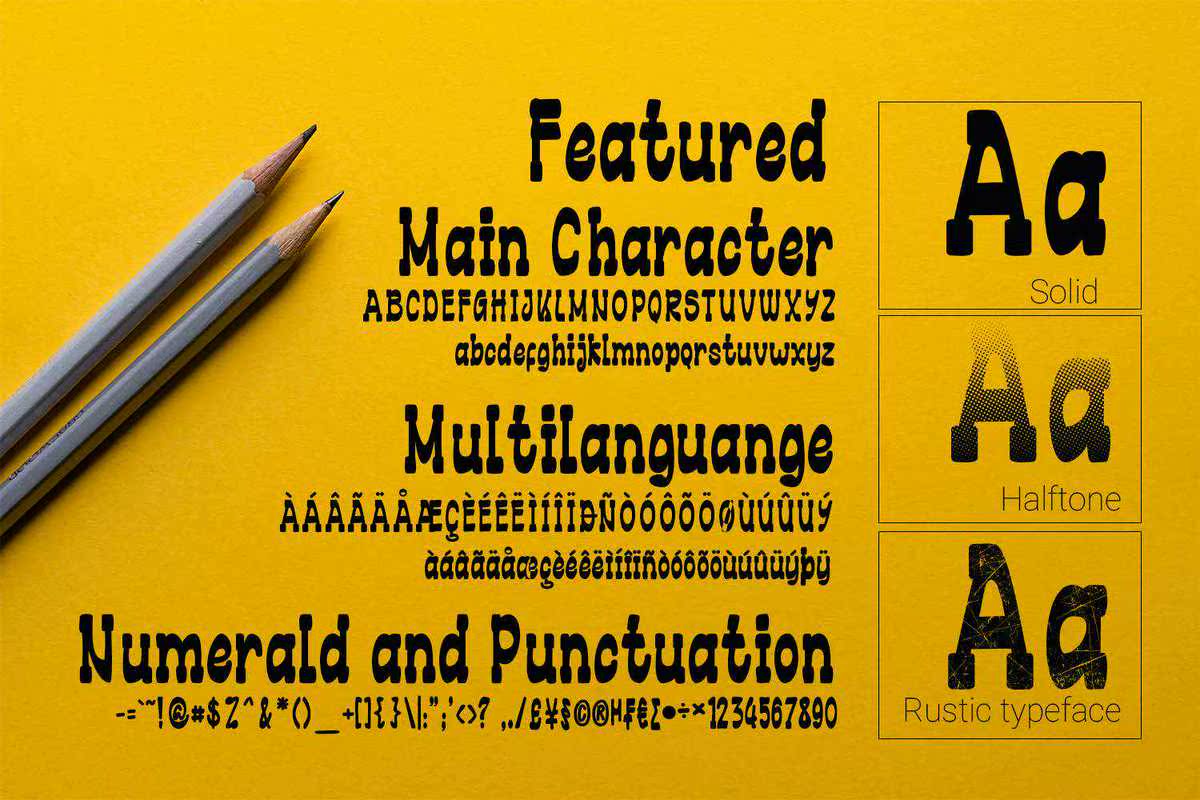
BoldGrunge是一款具有强烈纹理的高分辨率字体。它是一款带有Ashabby、Worn和Stained外观的超常规的Grunge设计。它是一款规则、半色调和德鲁西风格的字体,适用于所有设计。BoldGrunge是一款具有强烈纹理的高分辨率字体。它是一款带有Ashabby、Worn和Stained外观的超常规的Grunge设计,WOR和STAINED外观可完成非常普通的设计。它是一种规则的、半色调的和德鲁西风格的版本,可使所有设计完美无瑕。